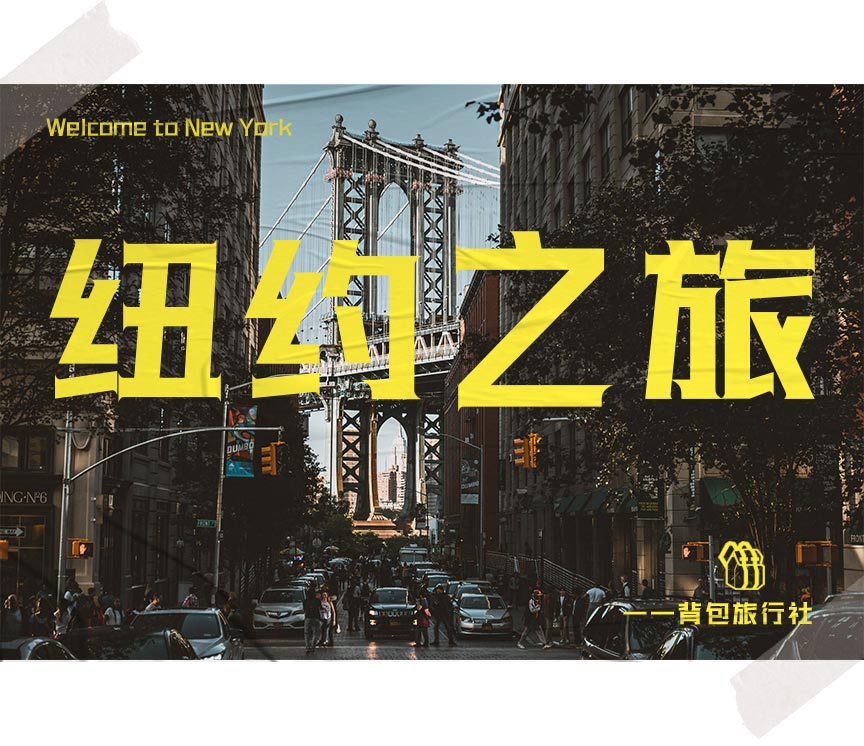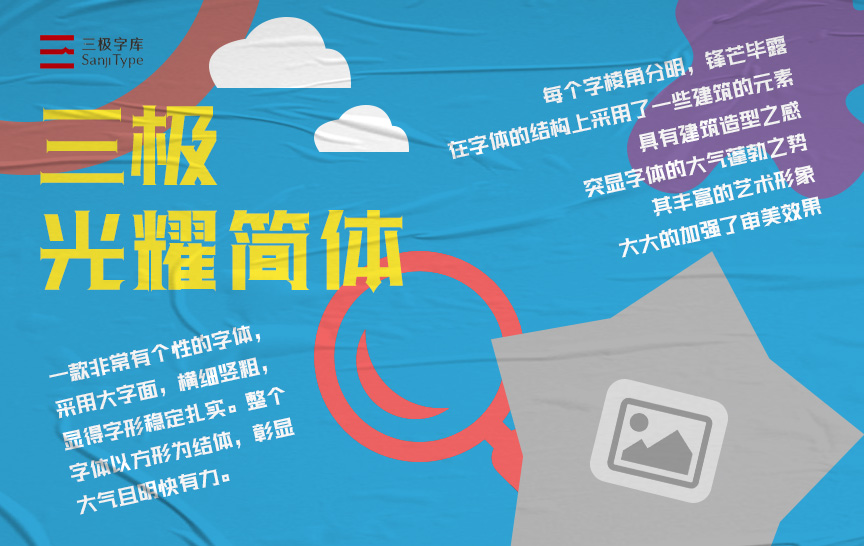
三极光耀简体家族
罗碧霞,庞丽珊
三极光耀简体是一款非常有个性的字体,采用大字面,横细竖粗,显得字形稳定扎实。整个字体以方形为结体,彰显大气且明快有力。每个字棱角分明,锋芒毕露。在字体的结构上采用了一些建筑的元素,具有建筑造型之感,突显字体的大气蓬勃之势,其丰富的艺术形象,大大的加强了审美效果。适用制作大型广告、海报,包括报刊杂志上的标题字,文艺类的书刊、品牌广告和产品包装设计,以及社交网络的个性化用字。适用媒介:杂志、书籍、广告、标志、宣传册、包装、影视、动漫、交互设计。